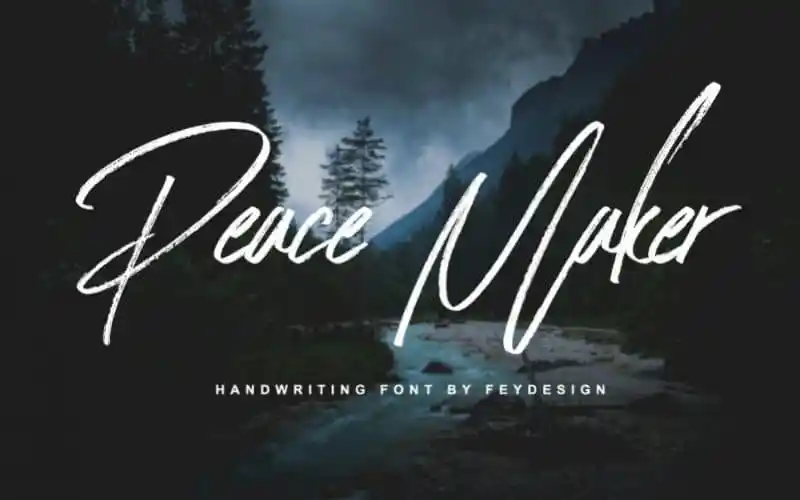
Peace Maker Brush Font – Fonte Grátis
Peace Maker Brush Font
A Peace Maker Brush Font é uma escolha perfeita para designers buscando uma solução com um estilo natural e elegante. Inspirada na mão dura dos artistas, esta fonte tem um flow de escrita que transmite seriedade ao mesmo tempo em que oferece um ar descontraído. Ideal tanto para personal branding ou invites nupciais quanto para propaganda, a Peace Maker Brush Font é uma coleção versátil e elegante. Desenvolvida por feydesign, ela se destaca como uma fonte de traços da canva suave e perfeita para headlines e designs com estilo de assinatura. Esta fonte tem uma capacidade única de trazer um toque distintivo às suas criações, seja em um layout respeitoso ou casual. Não é à toa que ela se destaca como uma opção ideal para projetos exigentes que precisam atingir e agradar os olhos dos consumidores modernos. Com seu ar elegante e sua presença forte, essa fonte oferece aos designers um poderoso meio de destacarem seus trabalhos.